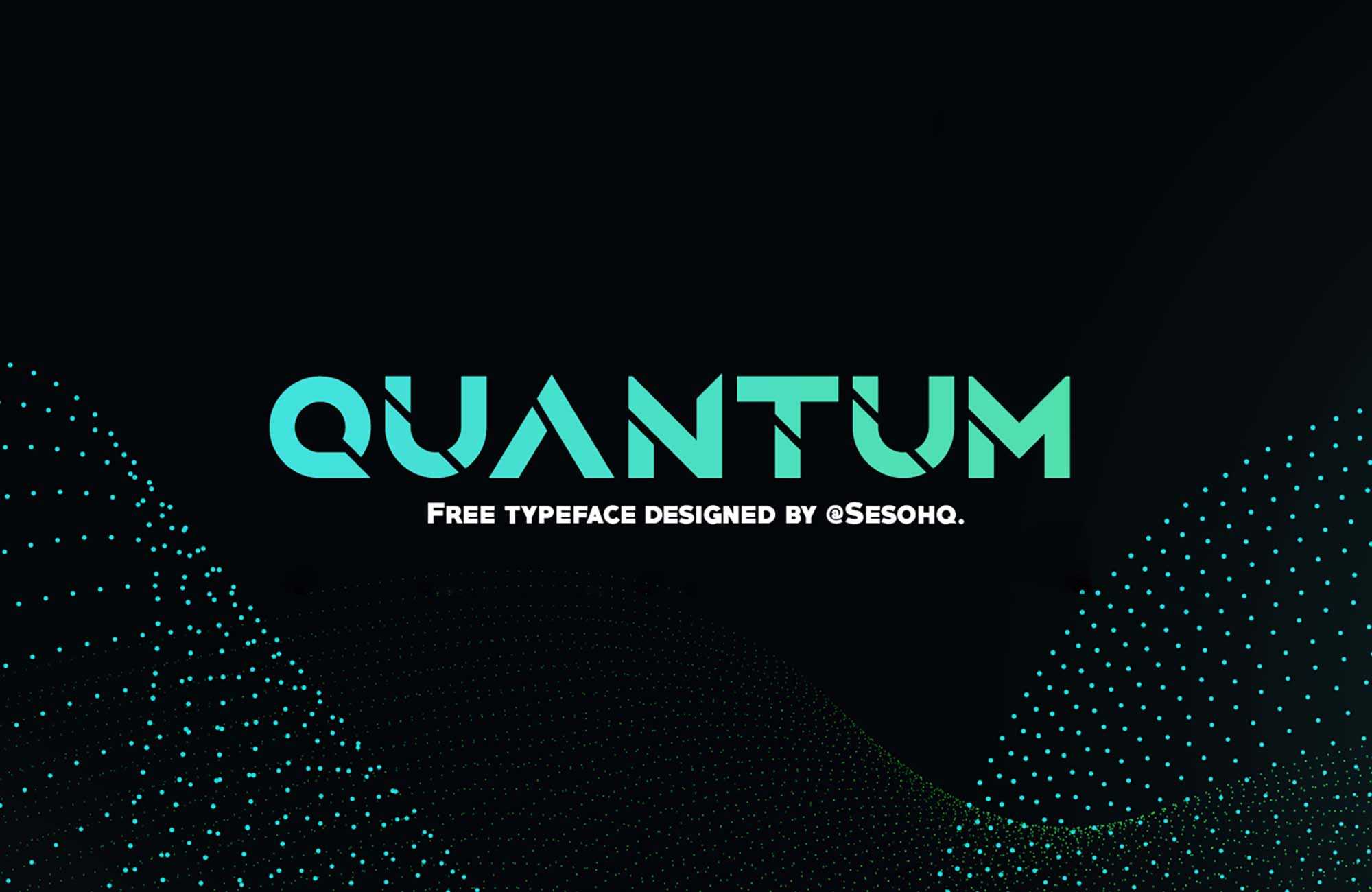
Quantum, em física, representa uma quantidade discreta de energia. Esta característica faz do Quantum uma fonte única e fascinante para explorar. Com a ajuda de Greg ‘Sesohq’ Ortiz, compartilhamos esta criação. Greg é um designer talentoso conhecido pelo seu trabalho em logotipos e fontes. Ele criou o Quantum, uma font que transmite precisão e modernidade, perfeitamente adaptada para uso em materiais científicos, tecnológicos ou quando você deseja um toque inovador em seu design. Este recurso gráfico gratuito oferece uma maneira de incorporar este conceito fascinante em seus projetos, sem precisar pagar uma fortuna. Seja você um designer ou criativo, a font Quantum pode ser a solução perfeita para aquele design que precisa de um toque de inovação e precisão.